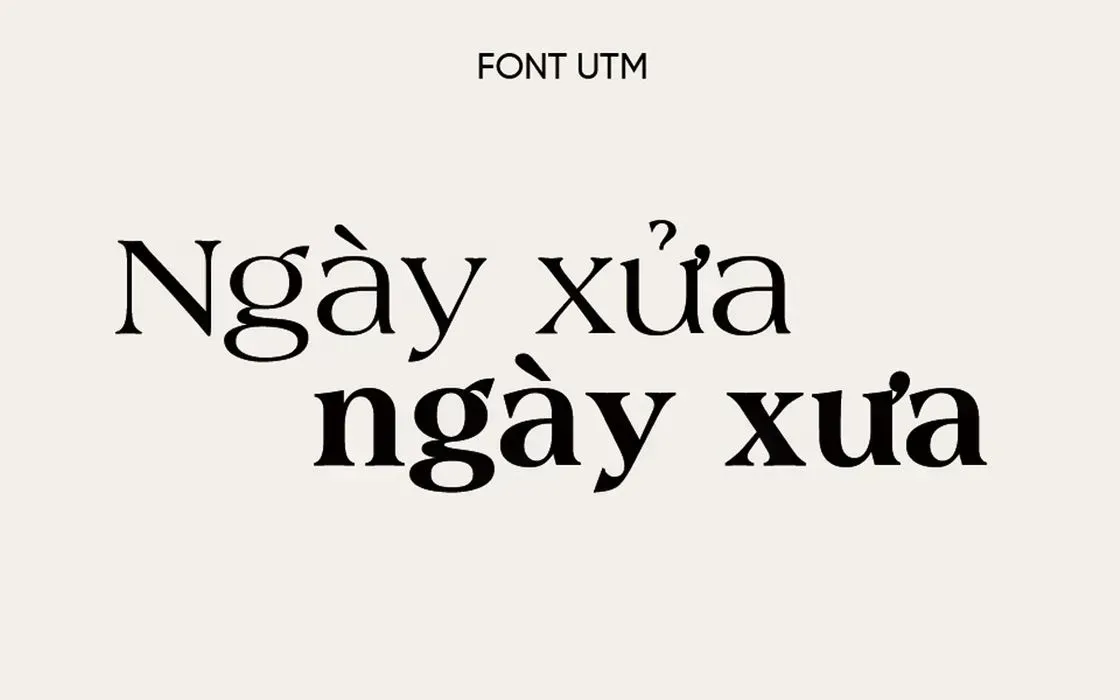
UTM Americana là một kiểu font serif (có chân) mang phong cách cổ điển nhưng không kém phần thanh lịch. Font sở hữu các đường nét thanh mảnh kết hợp với chân chữ mềm mại, tạo nên sự duyên dáng và dễ đọc trong mọi định dạng. Thiết kế chữ có sự chuyển đổi tinh tế giữa các nét dày và nét mảnh, giúp từng ký tự trở nên mềm mại, nhã nhặn nhưng vẫn toát lên sự sang trọng và chuẩn mực.
Nguồn gốc của font Americana đến từ kiểu chữ “ITC Americana”, do nhà thiết kế nổi tiếng Richard Isbell phát triển vào những năm 1960. Font được sử dụng rộng rãi trong các ấn phẩm in ấn cao cấp, sách báo, tạp chí và các sản phẩm thương hiệu mang hơi hướng cổ điển của Mỹ.
Phiên bản Việt hóa UTM Americana được thực hiện bởi nhóm Urban Type Management (UTM) – một trong những đơn vị hàng đầu trong việc Việt hóa font chữ tại Việt Nam. Font đã được bổ sung đầy đủ hệ dấu tiếng Việt, đảm bảo hiển thị chính xác và đẹp mắt trên cả màn hình lẫn bản in, đồng thời tương thích với các phần mềm như Photoshop, Illustrator, Word, PowerPoint...
Với vẻ đẹp hoài cổ, chỉn chu và dễ đọc, UTM Americana là lựa chọn lý tưởng cho các thiết kế thương hiệu truyền thống, báo chí, thiết kế sách, hồ sơ năng lực hoặc các ấn phẩm cần sự tin cậy và chuẩn mực trong hình thức trình bày.